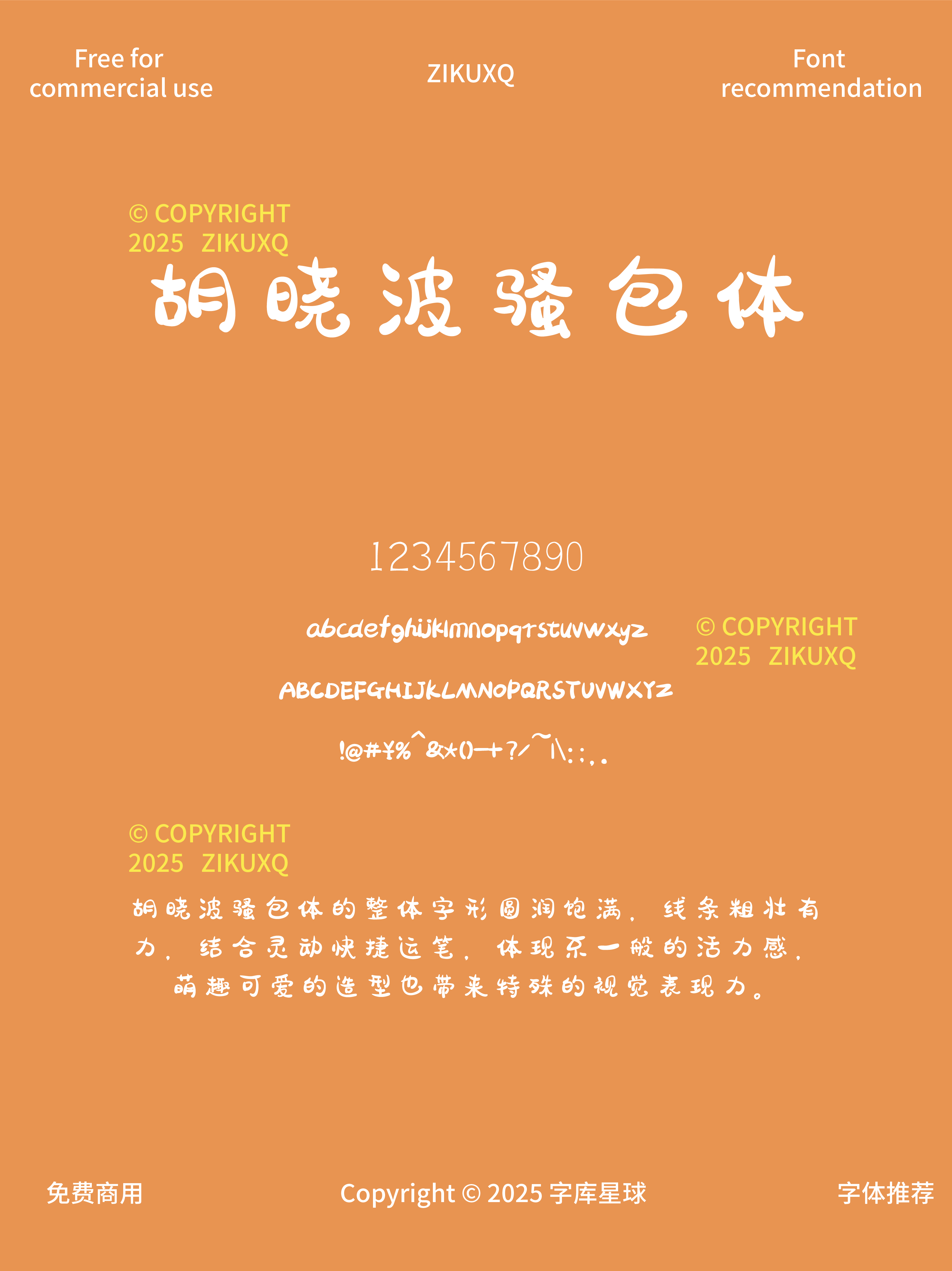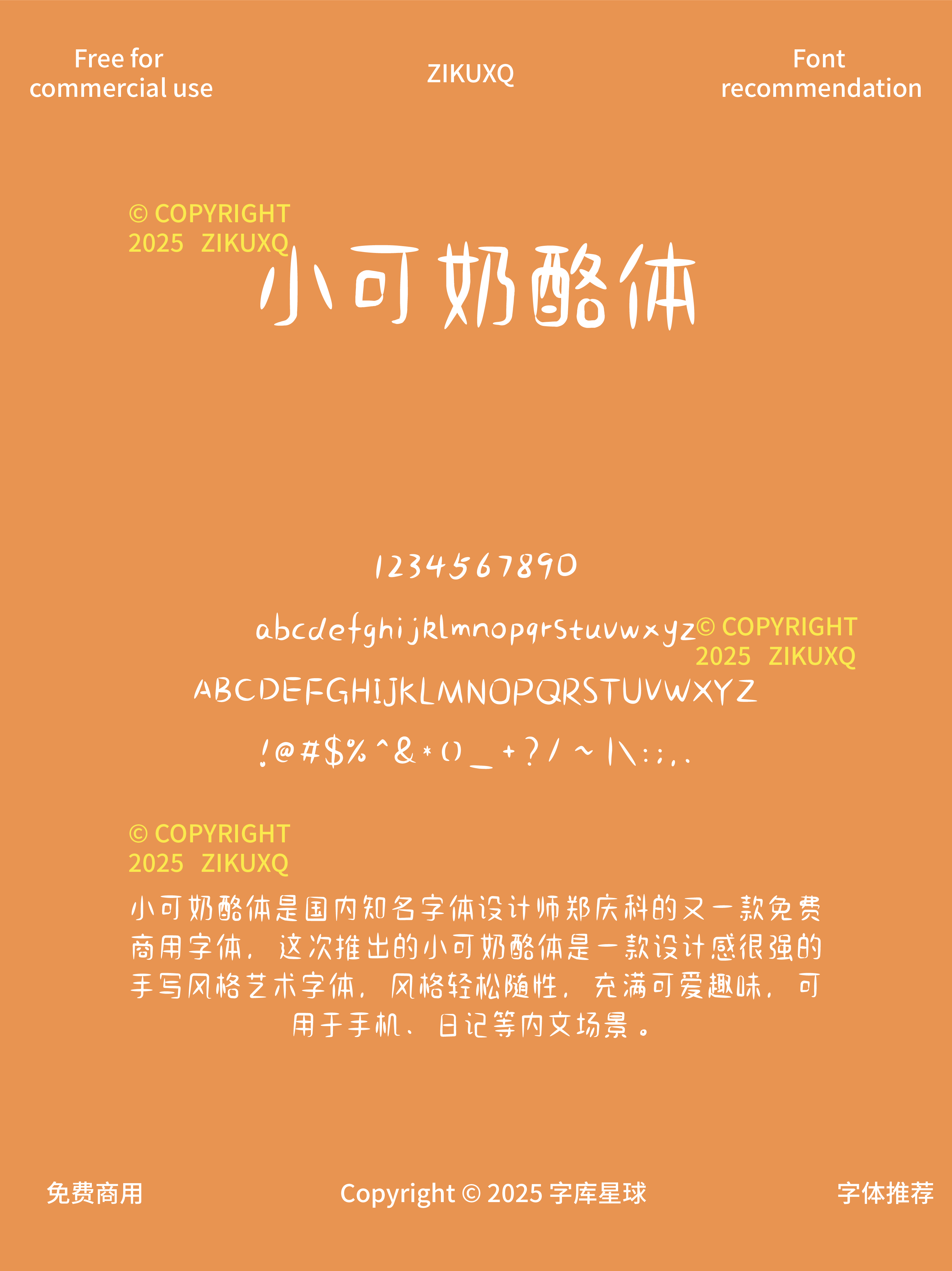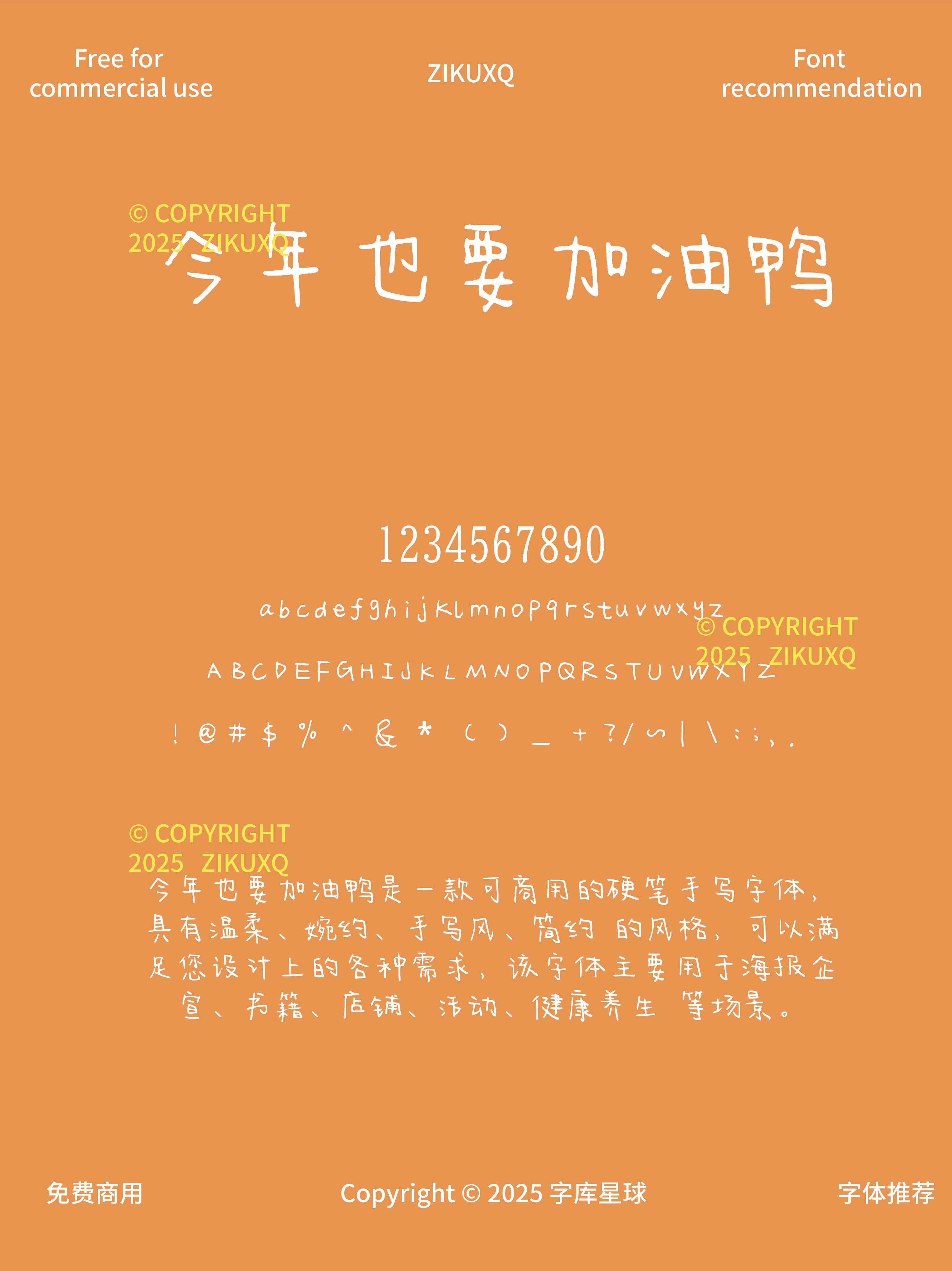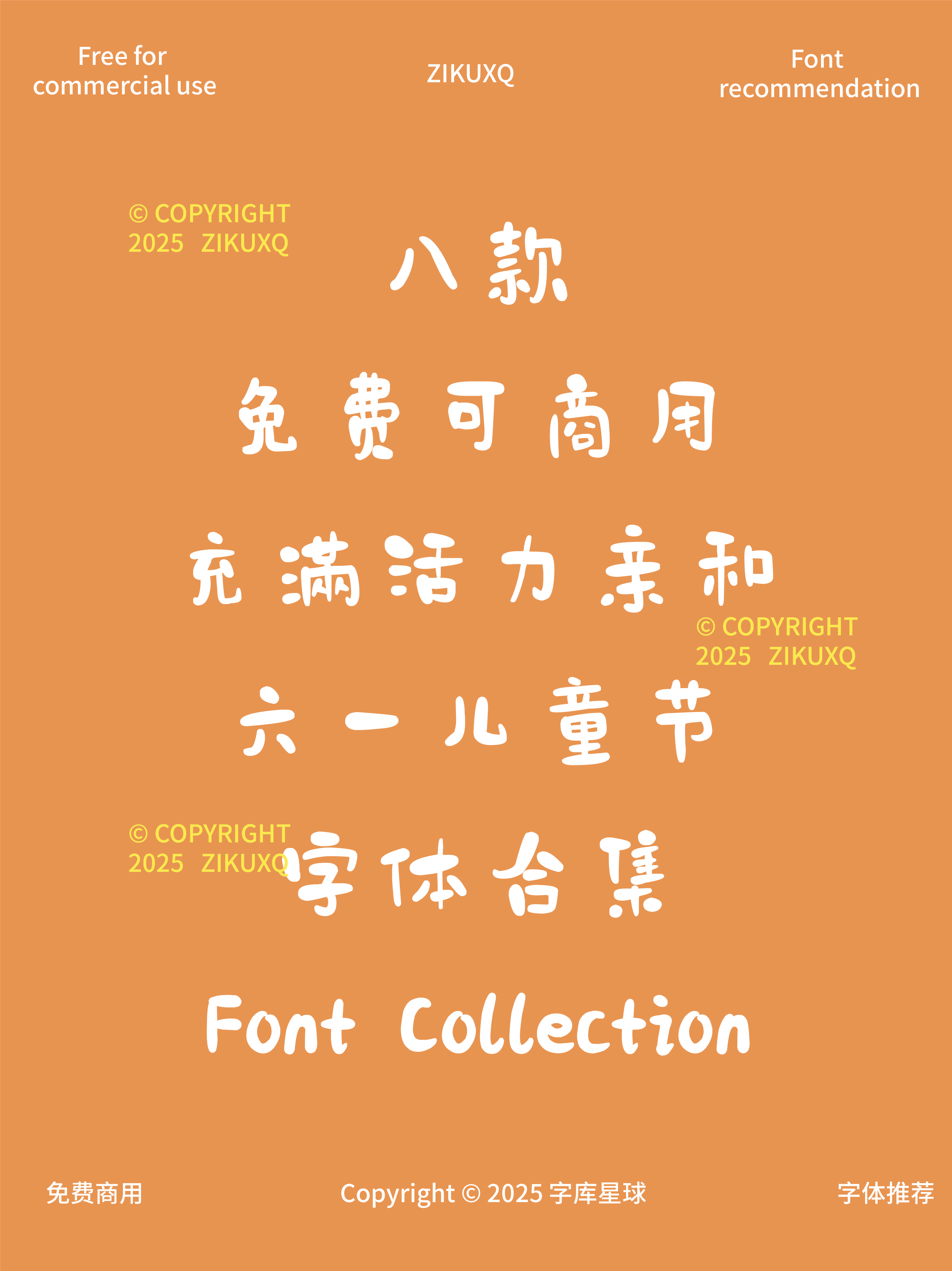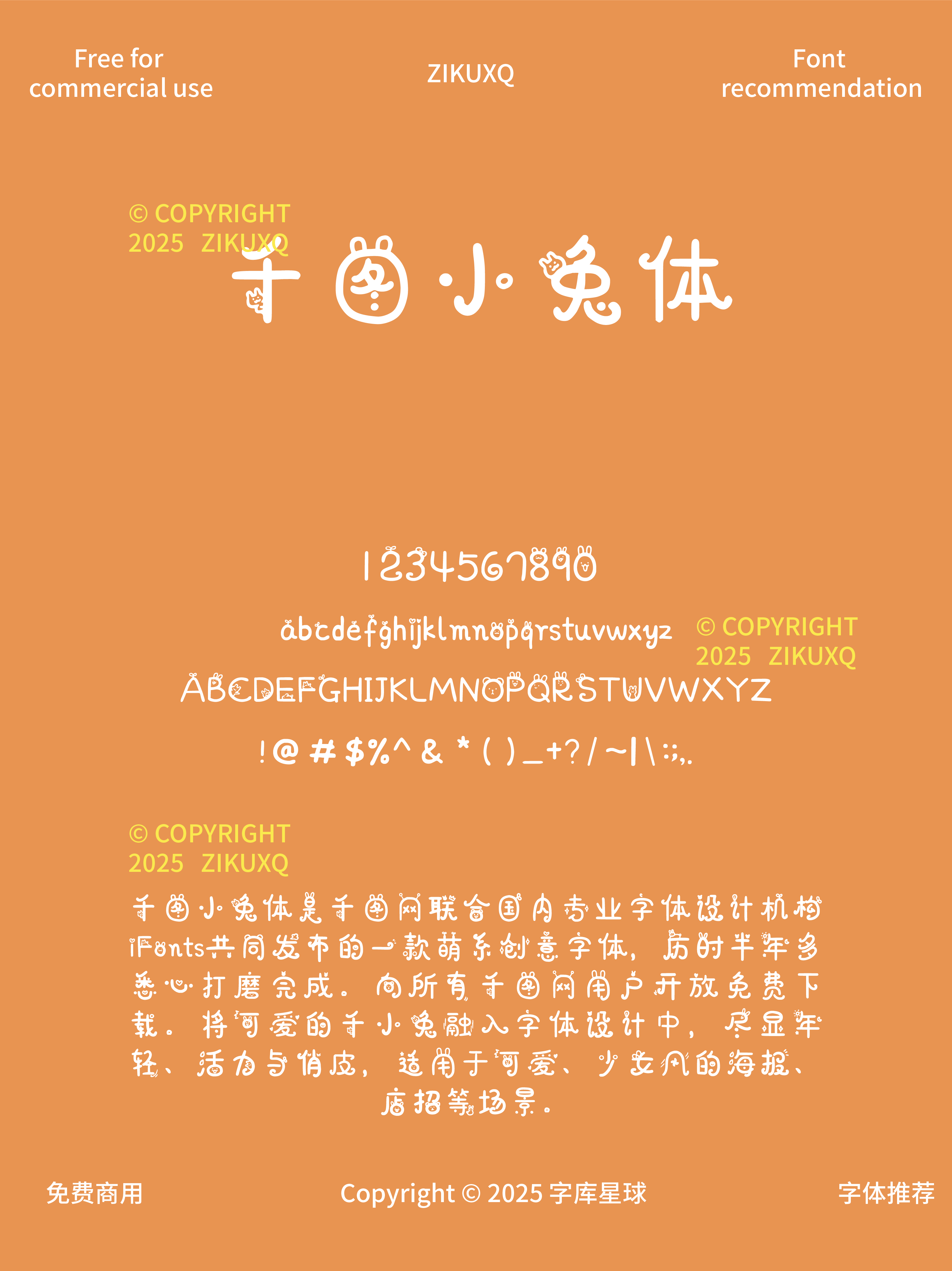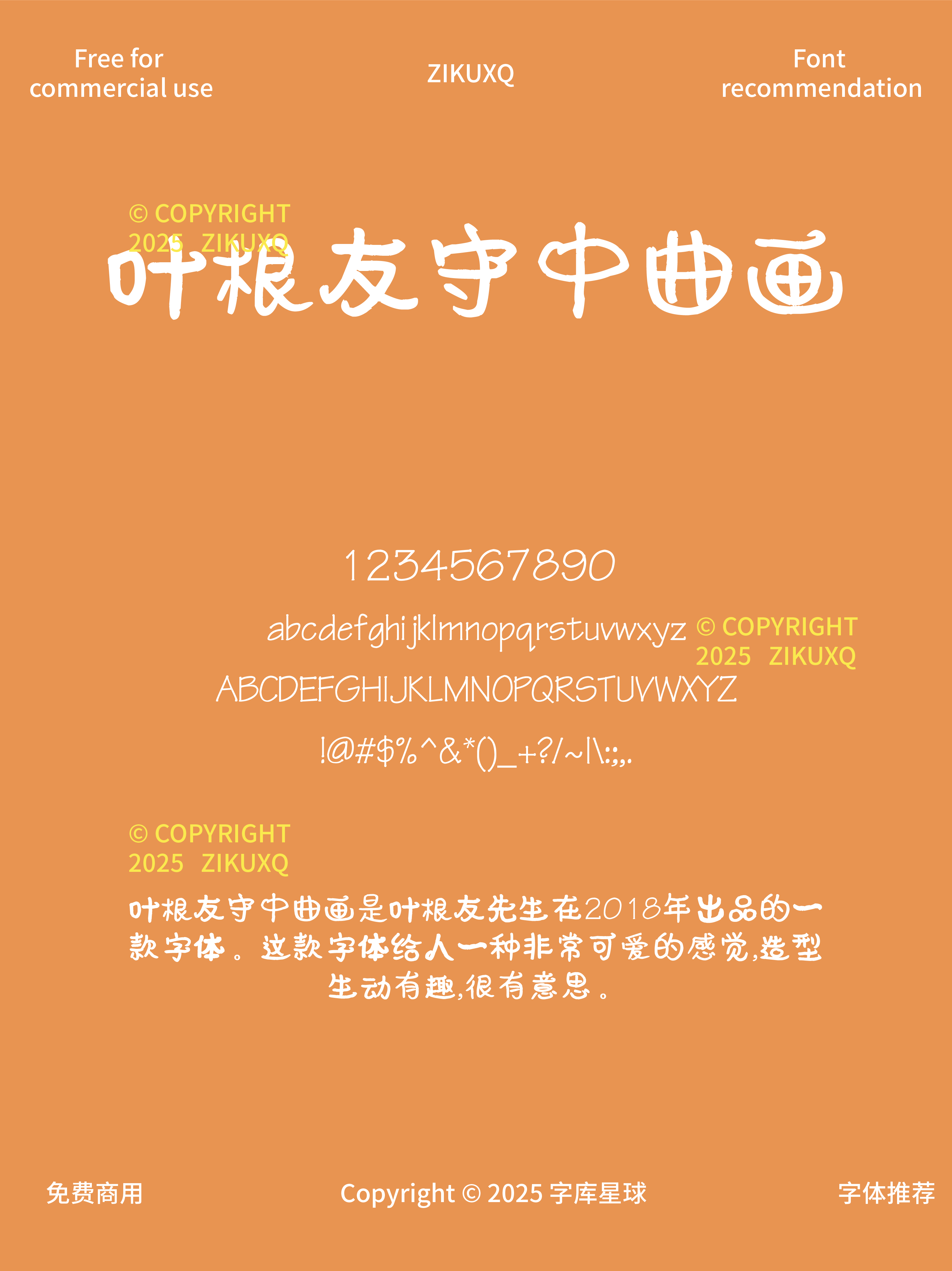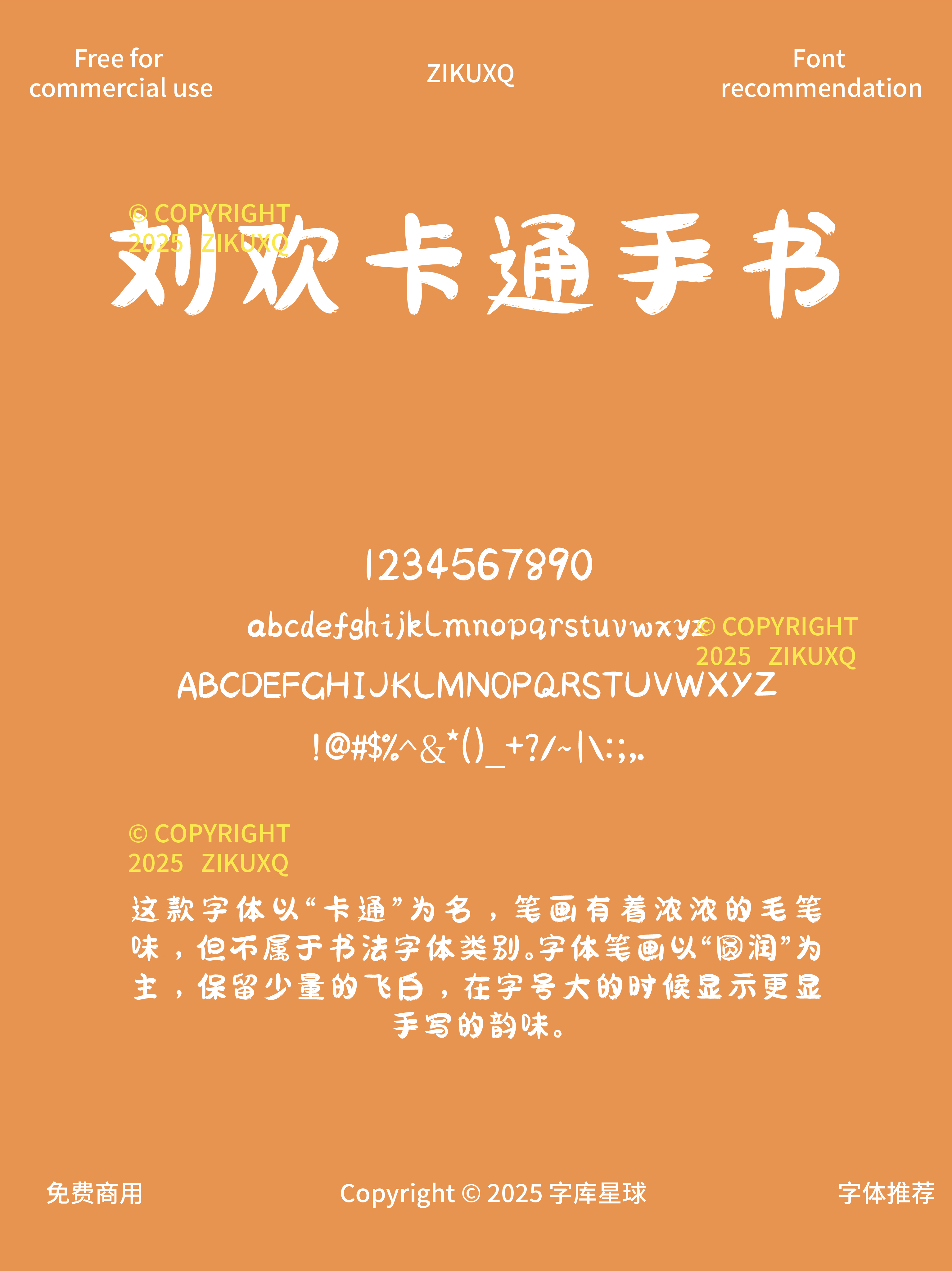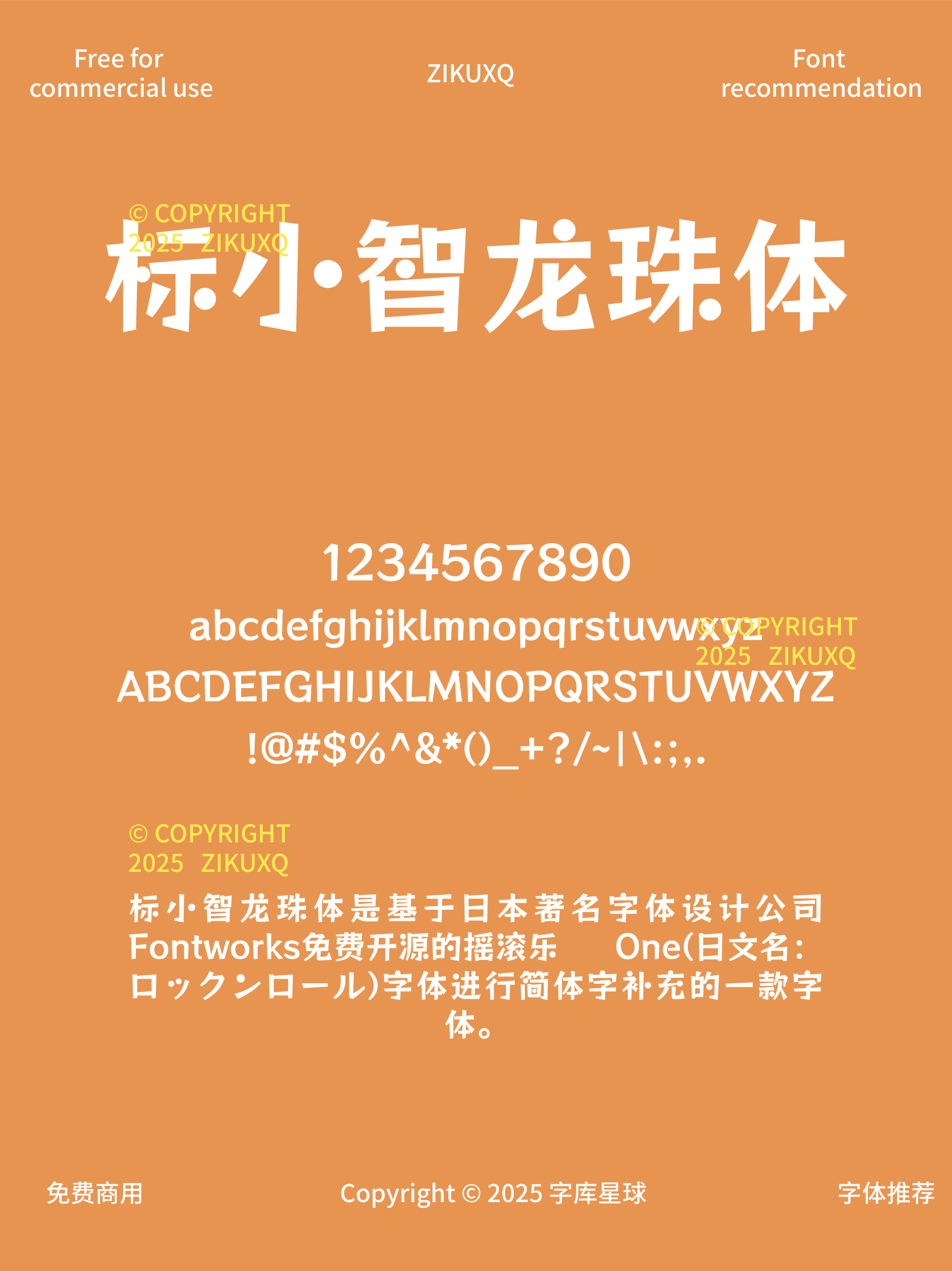
八款免费可商用充满活力亲和的六一儿童节字体
六一儿童节马上就到啦!是不是正在为儿童节相关的设计项目找合适的字体而发愁呢?别担心,今天我就给大家分享 8 款免费可商用,且充满活力与亲和力的儿童节字体,轻松为你的设计增添童趣~
生动活泼、圆滑 q 弹,小巧玲珑的艺术字体一枚~线条有粗有细,视觉感超棒,无论是文化宣传设计,还是产品包装设计,都能完美适配,为设计注入可爱活力。
书写笔画随意放松,变化丰富,卡通趣味浓厚,装饰色彩极强。在艺术设计、包装印刷等领域都能大显身手,让设计充满童真。​